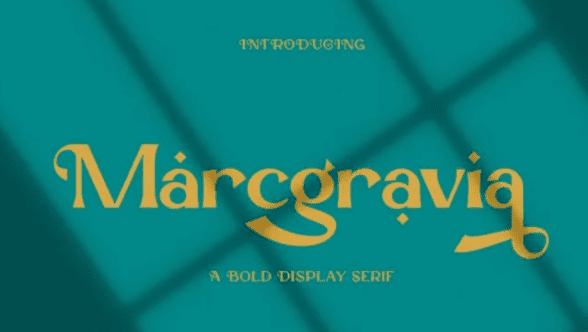
[Fontbundles] Marcgravia Font (2021)
Поприветствуйте наш новый смелый шрифт с засечками "Marcgravia".
Marcgravia - это стильный, современный и роскошный шрифт с засечками. Он возвысит каждое ваше творение.